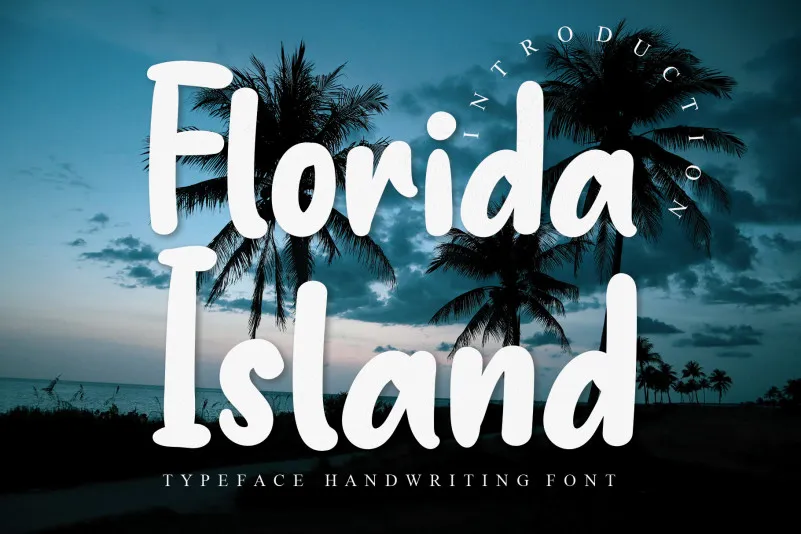
A Florida Island Display Font é uma escolha perfeita para quem deseja criar designs vibrantes e charmosos. Essa fonte abraça elementos fun e maciços dos caracteres, criando um estilo que combina alegria e elegância de maneira única. Ideal tanto para branding, quanto para produtos em embalagens, convites, frases memoráveis, camisetas personalizadas, rótulos, posters e logotipos, ela oferece uma linguagem visual dinâmica e irresistivelmente atrativa. Perfeito para quem busca dar um toque especial a seus projetos visuais, este fonte irá garantir que seu design seja o destaque em qualquer cenário.